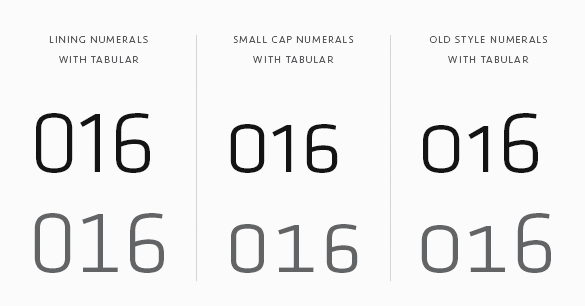
Schriftfamilie Klavika
Ich habe eine Frage zur Schriftfamilie Klavika. In Produktbroschüren meiner Firma wurden Varianten von Klavika verwendet (KlavikaBasic-Bold, -Light, -Medium, -Regular). Während diese Schrift grundsätzlich gefällig aussieht, sind einige Teile schlicht und einfach indiskutabel gestaltet, und ich weiß nicht, ob dies an der Schriftart liegt oder schlampige Arbeit des Grafikers ist. Entweder müssen wir uns eine andere Schriftart aussuchen oder der Grafiker muß sorgfältiger arbeiten. Hauptsächlich geht es um zwei Probleme:
- Innerhalb von Tabellen weisen gleich lange Zahlen unterschiedliche Breiten auf, was bei der Verwendung von Tabellenziffern nicht geschehen sollte. Vor allem die Ziffer 1 scheint schmäler zu sein, aber wie man am angehängten Bild sieht, ist dies nicht das einzige Problem. Daher meine Frage: Haben die Ziffern bei Klavika, so wie es bei Tabellenziffern sein sollte, die gleiche Breite oder nicht?
- Bei Formeln werden griechischen Buchstaben als Formelzeichen für Winkel in einer anderen Schrift gesetzt, welche nicht so recht paßt. Die konstanten Strichstärken von Klavika und die variablen Strichstärken der Formelzeichen ergeben ein häßliches Bild. Gibt es bei Klavika griechische Buchstaben, die zum Rest des Textes passen oder nicht?
die Klavika gibt es in 2 Versionen, Klavika Basic ist ohne Tabellenziffern.
D.h., entweder hat euer Grafiker die basic Version, oder er hat die Vollversion aber die Tabellenziffern nicht eingesetzt.
Die von euch benötigten griechischen Buchstaben scheint sie allerdings nicht zu bieten.
die klavika basic hat keine tabellenziffern, die klavika »full« jedoch schon
mit griechisch schaut’s allerdings nicht so gut aus, da nur latin extended abgedeckt ist. da müsste man sich mit einer anderen – eventuell sogar ähnlichen – serifenlosen helfen. eine antiqua mit strichstärkenkontrast wie in deinem beispiel geht natürlich gar nicht.